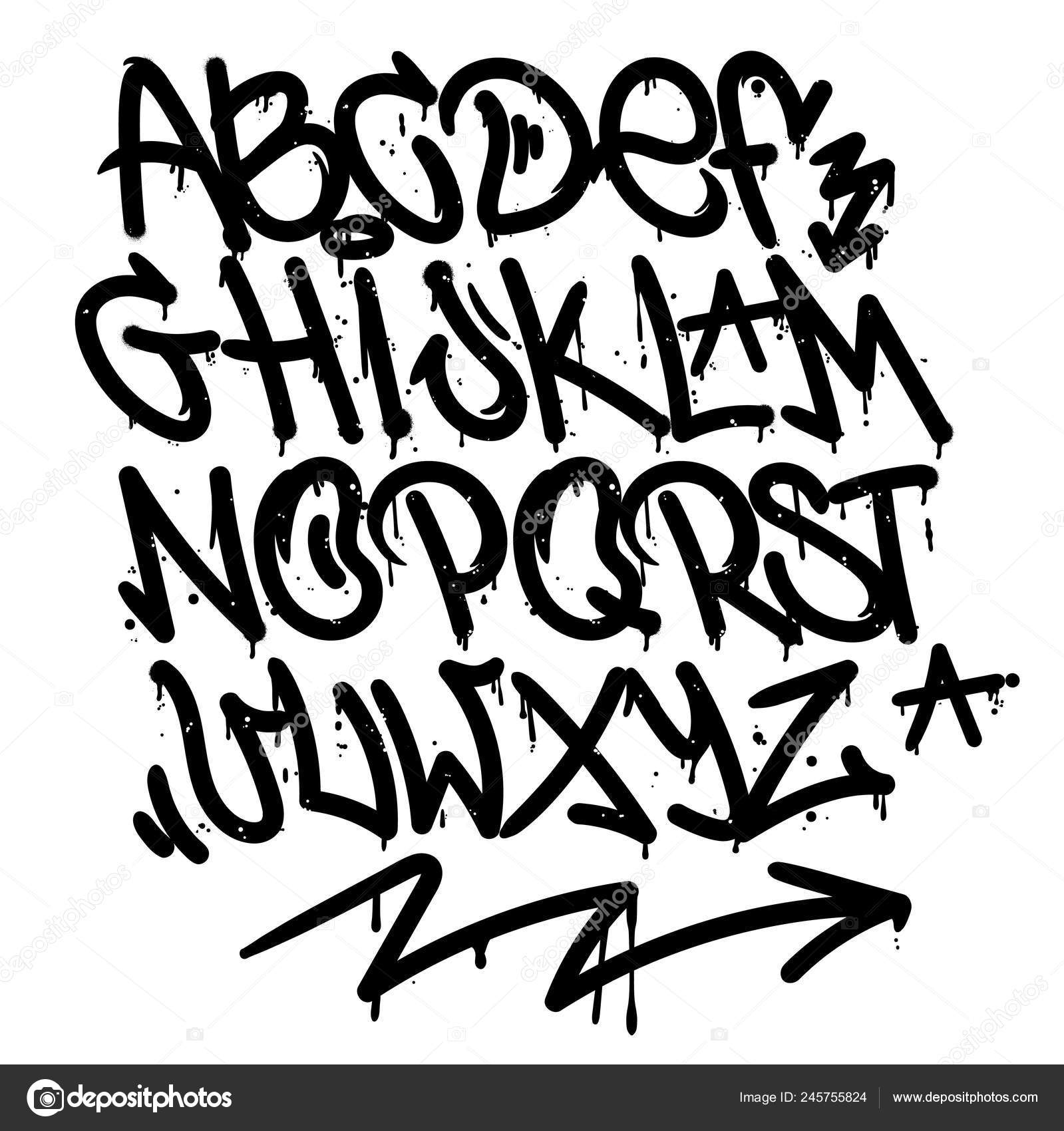
уличная живопись или высокое искусство, как применять в дизайне
Граффити шрифты изначально предназначались для надписей во времена Древней Греции и Рима. В современной культуре граффити больше существует как знак выражения протеста или используется для того, чтобы сказать — «Здесь был Killroy».
В то время как многие рассматривают граффити как акт вандализма, в цифровом виде такие шрифты могут придать работе новый уровень уникальности и привлекательности. Для проектов, которые должны заметить, применение graffiti fonts будет очень кстати.
История граффити шрифтов
Граффити десятилетиями разрушали наши города, «украшая» стены и двери жилых домов, заборы, тротуары и любые свободные уголки.
Часто городская живопись рассматривалась как посягательство на частную собственность и становилась предметом обсуждения общественности.
Интересно: Рост городской, уличной культуры и моды наряду с музыкальными жанрами хип-хопа и рэпа привел к увеличению популярности граффити как вида искусства, в который оказались вовлечены художники мейнстрима, а также уличные живописцы.
По сути, граффити обладает многими элементами, которые люди ищут в шрифтах, такими как креативность, драматизм, цвет, экспрессия и привлекательность. При определенных обстоятельствах это может быть полезно. Но найти действительно хорошие graffiti fonts сложно. Они должны быть с хорошей читаемостью, удобные для пользовательского интерфейса и подходящие для нескольких проектов.
Типографика для привлечения внимания
Один из самых простых способов привлечь внимание — сделать акцент на определенных словах, предложениях или абзацах. Можно подчеркнуть текст, написать его жирным, увеличить буквы, заострить углы, сместить центр.
Все эти акценты присутствуют в граффити шрифтах, делая их привлекательными для веб-дизайнеров и креативных пользователей соцсетей.
Важно: С современными текстовыми редакторами легко усилить необычные качества фонтов, придав им больше оригинальности и новых черт.
Цвет как элемент дизайна
Психология цвета — это еще одна область, работающая на привлечение внимания. Уличные граффити как нельзя лучше подходят для экспериментов с оттенками, тенями и градиентами.
Комбинирование дизайна сайта, стилей и цветов фонтов — нелегкая задача. Можно оставить оттенок шрифта по умолчанию, но лучше что-то изменить, чтобы получить больше визуальных результатов для выбора.
Вот как люди воспринимают основные цвета:
- Красный – страсть, любовь, волнение, сила, агрессия, опасность;
- Зеленый – баланс, безопасность, окружающая среда, рост, производительность;
- Синий – спокойствие, освежающий, уверенность, авторитет, навязчивый, холодный;
Конечно, на цветовом круге есть множество других цветов, создающих иное восприятие в сознании зрителя.
Для граффити шрифтов лучше выбирать яркие, будоражащие, экспрессивные оттенки.
При правильном использовании граффити шрифты могут стать находкой для вашего сайта, баннера или вывески.
Поместив сообщения о шрифтах в среду, которая меньше всего ассоциируется с «хорошим» дизайном, авторы хотели не столько прорекламировать Rentafont, сколько привлечь внимание к вопросу шрифтовой культуры и легальному использованию шрифтов в Украине.
Недавно коммуникационная кампания получила серебряный диплом конкурса Ukrainian Design: The Very Best Of.
Алексей Сальников, дизайн-стратег Numo Team:
Это не столько коммуникационная кампания, сколько наше небольшое исследование уличной визуальной культуры украинских городов. Уличные объявления обычно критикуют за яркое оформление и засорение визуальной среды. Но навязчивость и грубые приёмы вёрстки вроде растянутых шрифтов прекрасно работают на выполнение задачи — «выжить» и докричаться до потребителя. Вместо критики мы попробовали прощупать границы между профессиональным и вернакулярным (то есть «народным», непрофессиональным), чтобы найти в этой маргинальности источник вдохновения и что-то родное сердцу.
Саша Быченко, арт-директор Numo Team:
Это может показаться очень странным решением: говорить о шрифтах и практике их использования там, где об этом заботятся меньше всего.